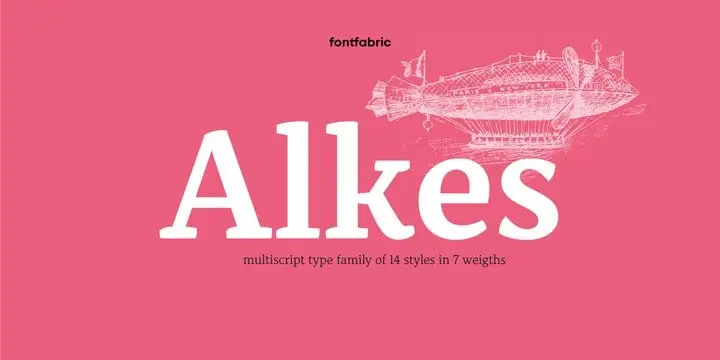
A Alkes Serif Font oferece uma sensação poética de elegância na tipografia serifada, inspirada nos cosmos e seu vasto universo. Seu nome lembra um asteroide distante no céu noturno, mas é esse espaço infinito que permeia cada traço dessa fonte única e bem definida. Desenvolvida originalmente como uma tese de graduação, a Alkes Serif conquistou sua posição nas páginas da publicação. Ela se destacou por harmonizar três scripts – o latim, grego e cirílico. Com um x-height generoso, espaçamento entre as letras ampliado, e contrastes sólidos angulares em seus contornos abertos, a fonte oferece uma aparência que combina perfeitamente tanto no digital quanto na analogia. Suas características mais belas aparecem claramente quando usada em tamanhos maiores. Este equilíbrio entre o detalhe chamativo e a estrutura calligráfica do texto, combinado com serifs não simétricos, torna a Alkes perfeita para headlines. Esta fonte é uma escolha ótima para editoriais e publicações onde longos textos são fundamentais. Seu design reflete o equilíbrio entre tecnologia e arte, dando vida aos seus desenhos no papel de modo que eles sejam elegantes e legíveis, independentemente do tamanho ou contexto.